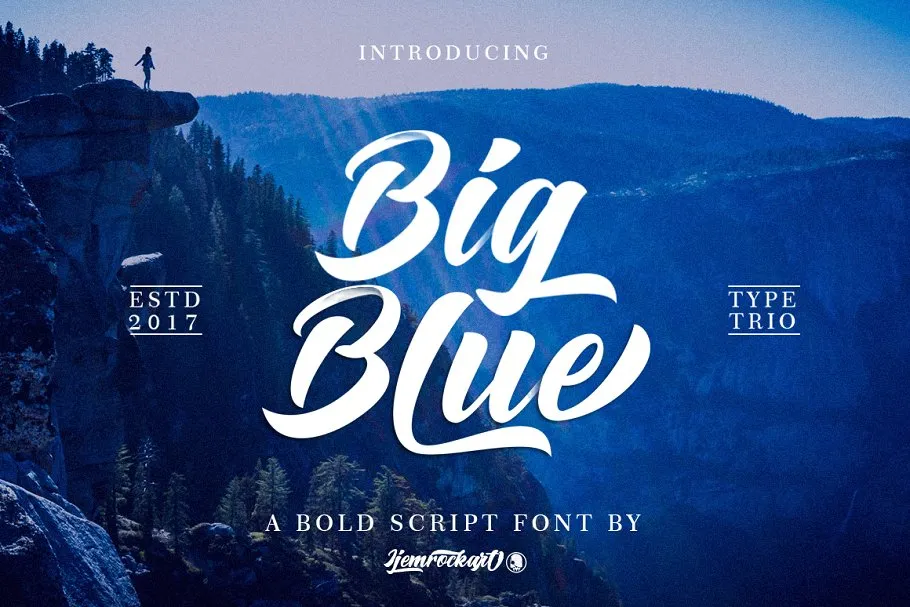
Aqui está uma descrição para a página de download da font ‘Big Blue Bold Script Font’, mantendo o tom informativo e convidativo: Introduzimos ‘Big Blue Bold Script Font’, uma fonte script bold com um estilo de traço brush. Ideal para quem busca um tipo desse formato, este é perfeito para aplicar em sua obra. ‘Big Blue Bold Script Font’ tem um aspecto elegante e orgânico, graças ao seu traçado cuidadosamente produzido à mão, repleto de imperfeições autênticas – com a correta mistura de brilho e rugosidade. Uma característica única é sua linha base que se move com um movimento leve e rico em vida. Com este tipo, acompanha-se uma fonte marcador super bem combinada e uma coletânea de benefícios de bonus de traçado swash. ‘Big Blue Bold Script Font’ é perfeito para logos, citações escritas a mão, embalagens de produtos, cabeçalhos, posters, material de merchandising, mídia social e cartões de cumprimentos. Essa fonte atende a uma variedade de necessidades designográficas, oferecendo opções criativas para sua próxima criação visual. Com ‘Big Blue Bold Script Font’, você pode criar mensagens impactantes em seus projetos visuais com um acabamento único e emocionante.